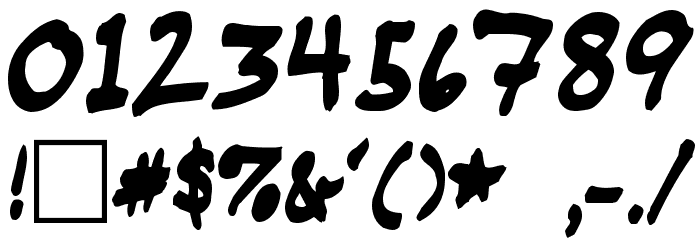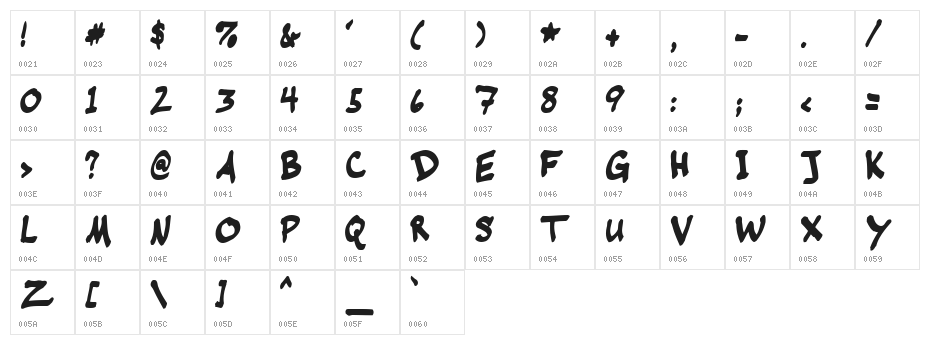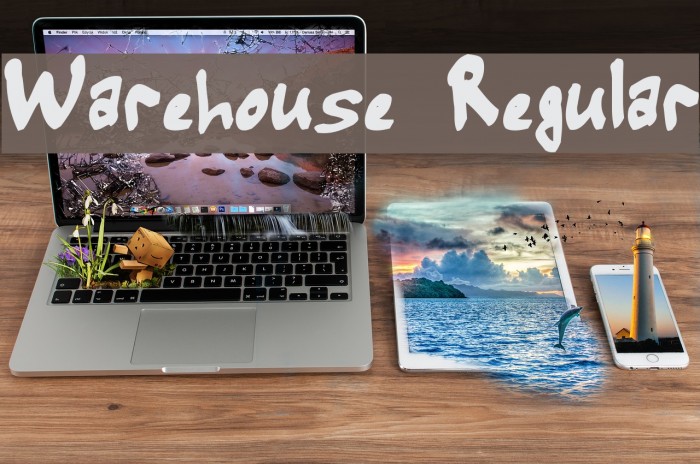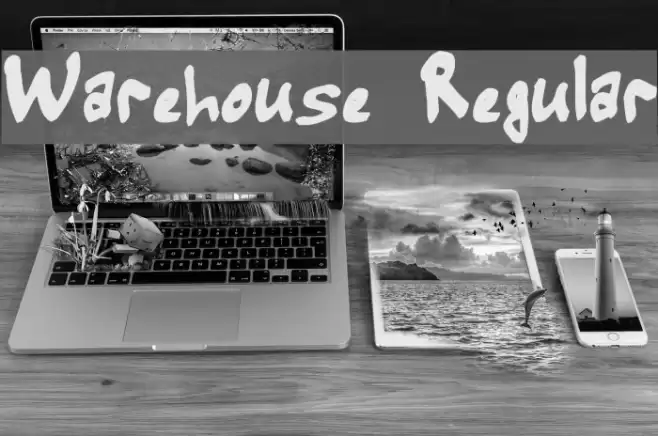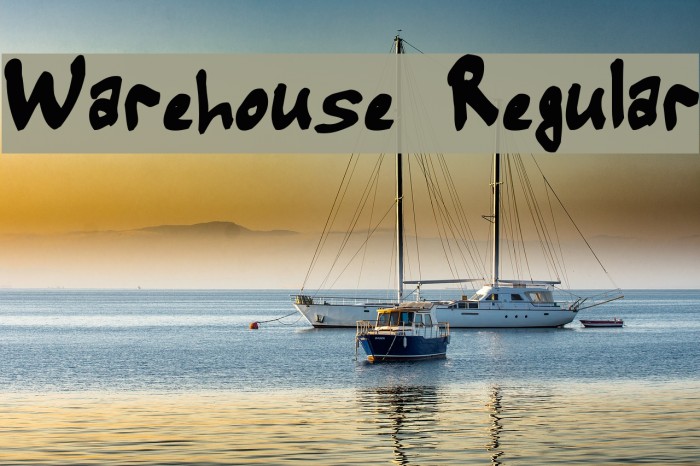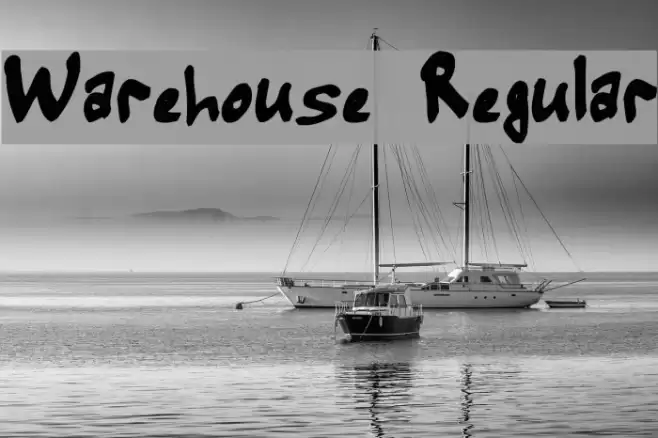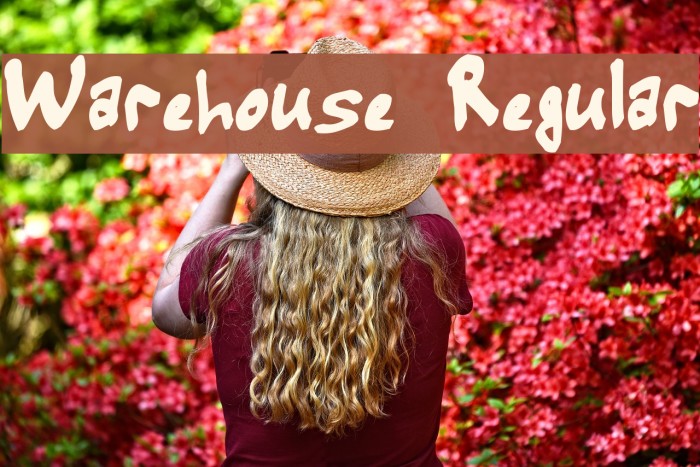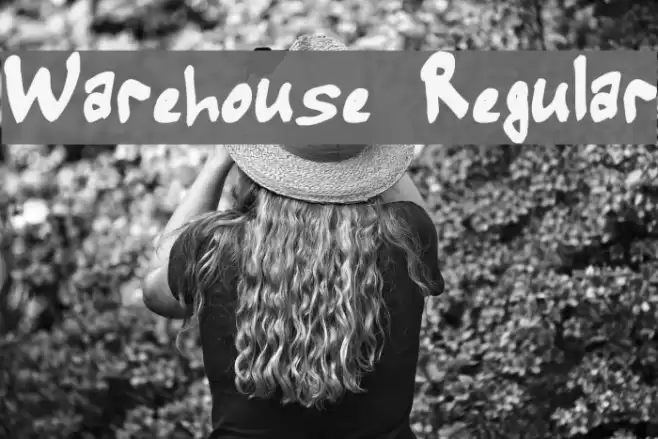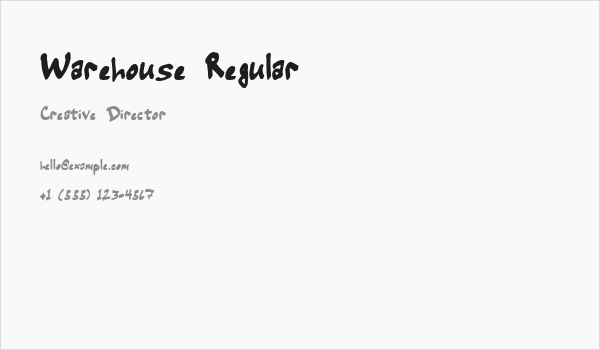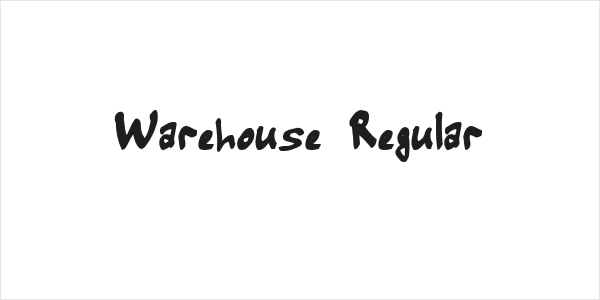
Warehouse Regular Font
| Cas d'utilisation | Headlines, Logos, Informal Text |
| Projets proposés | Ideal for greeting cards, posters, branding projects, and social media graphics where a personal and energetic touch is desired. |